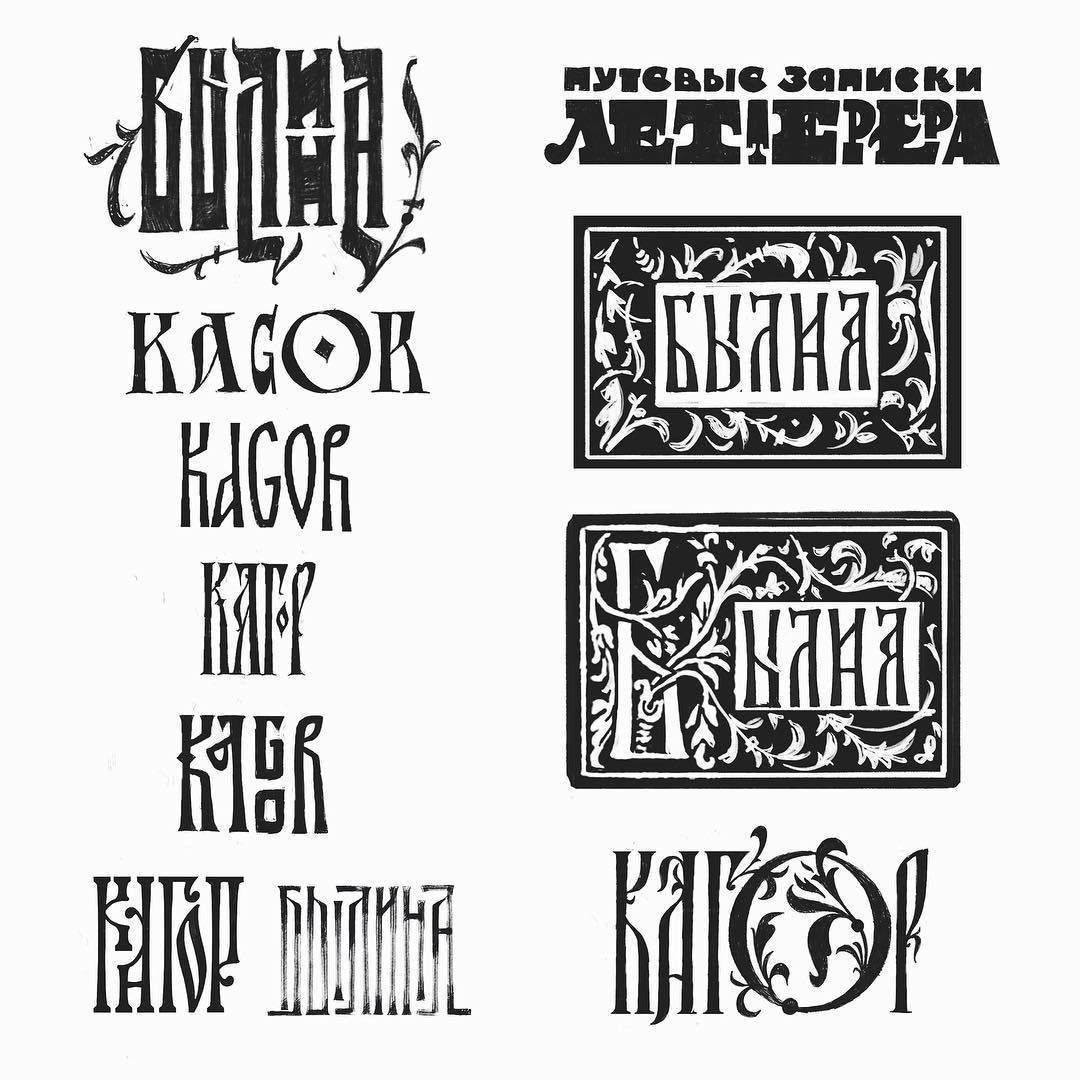
Старославянский шрифт (Курсовая работа) — TopRef.ru
«Старославянский шрифт»
Введение
Предметом исследования в курсовой работе служит предмет шрифты.
Непосредственным объектом изучения в работе выступает старославянский шрифт.
Цель работы – в соответствии с предметом изучить объект исследования, используя данные методологической, учебной и научной литературы.
Для достижения поставленной цели предполагается решить следующие задачи:
— описать историю возникновения и создания данного шрифта;
— дать сравнительную характеристику данного шрифта по сравнению с другими, близкими по написанию и произношению;
— определить основные закономерности
написания букв старославянского шрифта,
которые освящены в научно-исследовательских
работах.
Старославянский шрифт играет огромную роль в развитии славянской письменности. Памятники славянской письменности позволяют нам увидеть историю и социальные законы общества того времени. Без письменной речи сегодня невозможно представить человеческое общество. Мысль записанная — достояние не только современников, но и последующих поколений. Буквы, письмо — настоящая машина времени: с их помощью человечество можем везде «побывать», все «посмотреть», «вернуться» на тысячи лет назад или «заглянуть» в далекое-далекое будущее…
История создания старославянского шрифта
Древние славяне — большая группа племен, предков современных славянских народов Центральной, Южной и Восточной Европы, говоривших на языках, принадлежавших к индоевропейской семье.
Источниками по истории славян являются археологические и лингвистические памятники
Данные языкознания, гидронимии
и лингвистической географии связывает
древних славян с областью Центральной
и Восточной Европы.
Свидетельства
письменных источников подтверждаются
археологическими памятниками, которые
хорошо известны на территории бывшего
СССР (Поднепровье, Побужье. Поднестровье),
Польши, Чехословакии, Румынии. Болгарии,
Югославии. В процессе расселения славян
по огромным пространствам, имевшим
различное местное население, этническая
и языковая общность славян начала
постепенно разрушаться, что привело к
образованию существующих доныне
славянских группировок — западной,
восточной и южной/3/.
Исследуя возникновение славянской письменности впервые исторические свидетельства находим у болгарского писателя X века черноризца (монаха) Храбра, который посвятил началу славянской письменности маленькое сочинение — «Сказании о письменах», то есть о буквах/3/.
Храбр рассказывает, что в
древности, когда славяне были еще
язычниками, у них не было букв, они читали
и гадали «чрътами и резами». «Черты» и
«резы» — это разновидность примитивного
письма в виде рисунков и зарубок на
дереве, известного и у других народов
на ранних стадиях их развития.
Когда же
славяне крестились, продолжает Храбр,
они пытались записывать свою речь
римскими и греческими буквами, но «без
устроения», без порядка. Такие попытки
были обречены на неудачу, так как ни
греческий, ни латинский алфавит не был
пригоден для передачи многих особых
звуков славянской речи. «И так было
многие годы», — замечает первый историк
славянской письменности.
Так было до времени Кирилла и Мефодия.
Кирилл (светское имя Константин) и его старший брат Мефодий родились в византийском городе Фессалонике на побережье Эгейского моря (ныне Салоники в Греции), который славяне называли Солунь. Фессалоника была крупнейшим городом Византийской империи, в ее окрестностях издавна жило много славян, и, очевидно, еще в детстве мальчики познакомились с их обычаями и речью/2/.